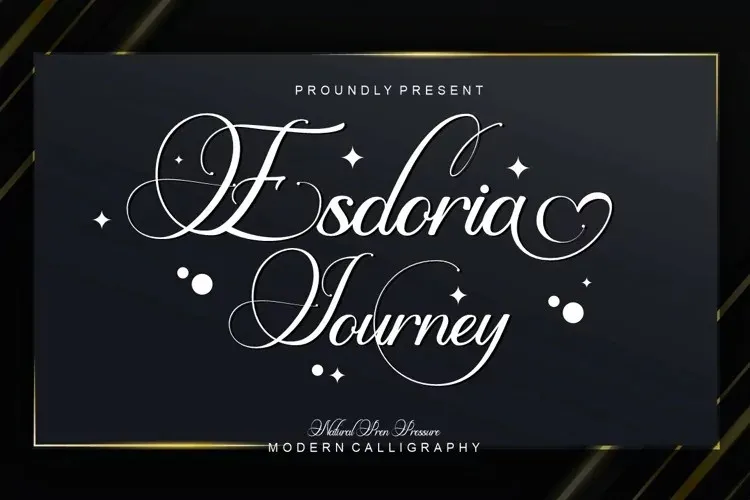
Esdoria Journey Font – Download Grátis
A Esdoria Journey é uma nova fonte à base de caligrafia que incorpora características vivas e arredondadas naturais, garantindo que qualquer ambiente, desde cartões de aniversário até editoriais jornalísticas, seja apropriado para o uso. Com mais de 100 alternativas (como ligaturas, caligrafias curvadas, opções alternativas e listas estilizadas), essa fonte irá te fazer parecer um grande escritor. Ela é perfeita para aqueles que valorizam uma linguagem criativa e elegante em seus projetos. Com a Esdoria Journey, você terá muitas maneiras de personalizar seu design, tornando-a uma escolha ótima para qualquer projeto que exige um estilo sofisticado e único. Não importa o tamanho do projeto ou a profundidade do trabalho, essa fonte é a solução perfeita para aqueles buscando uma nova abordagem estilizada no mundo das fórmulas.